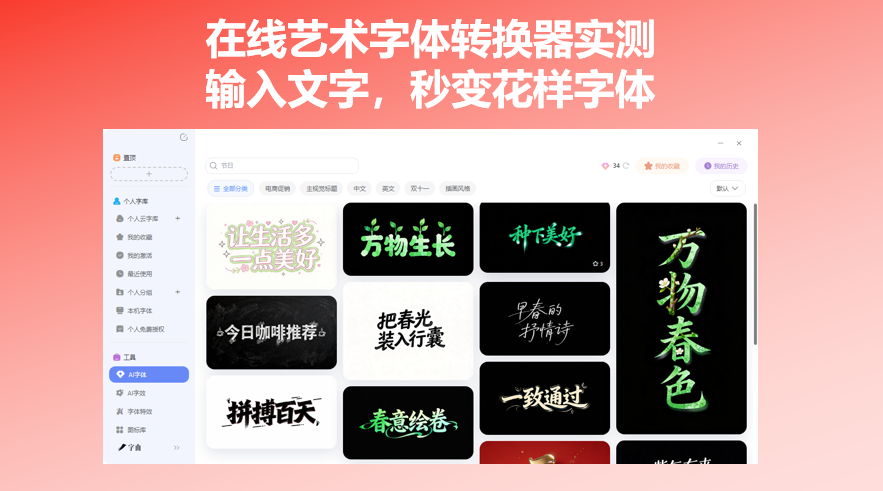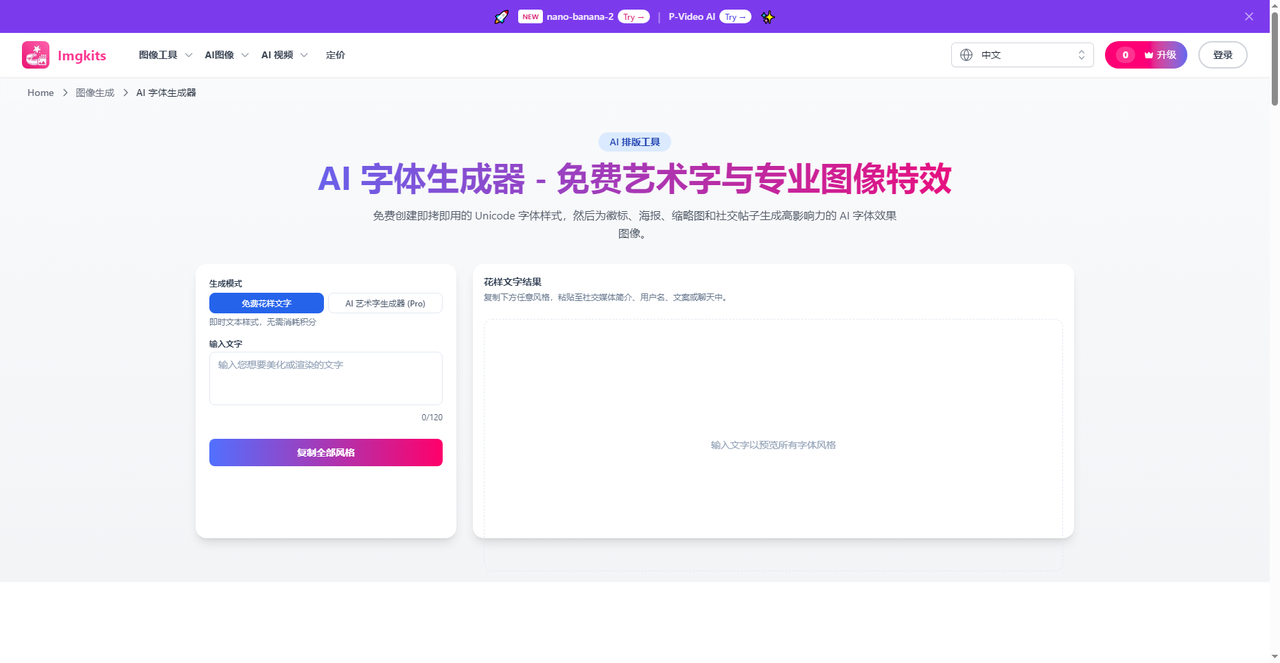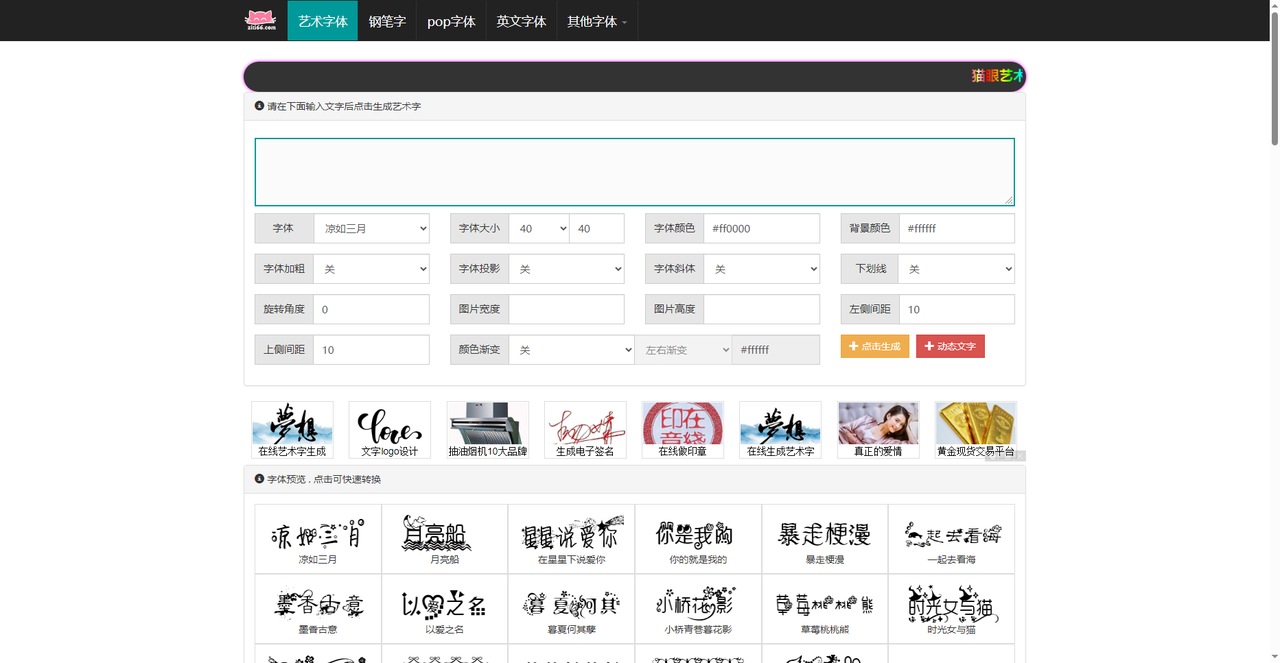
在线艺术字体转换器实测:输入文字,秒变花样字体
你有没有这种经历:文案想用花体字,结果只能打普通字体;做海报标题想要霓虹灯效果,打开PS调了半天还是觉得土土的;像给游戏账号改个特殊昵称,却没有好的办法。不过不用担心,这些问题一个在线艺术字体转换器就能搞定——输入文字,选个样式,复制粘贴或者下载图片,几秒钟完事。今天我的实测了5个不同风格的在线艺术字工具,从AI一键生成到参数自由调节,从Unicode花体到毛笔书法,覆盖了各种使用场景。喜欢的记得收藏!
字由是国内设计师用得最多的字体管理与AI平台之一。它的AI字体功能,本质就是一个在线艺术字体转换器——不需要你懂设计,选个模板,改几个字,10秒出图。打开字由客户端,在顶部“AI工具”里找到AI字体。里面按场景分好了类:国潮风、霓虹灯、金属质感、手写书法、电商促销……目前有400多种模板。操作很简单:先筛选你想要的风格,比如要做一张国潮海报,点“国潮风”分类,所有相关模板列出来;选一个顺眼的,点击“做同款”,在右侧输入框里把模板里的文字换成你自己的文案;点“立即生成”,等待10秒左右,系统就会生成一张带特效的艺术字图片。
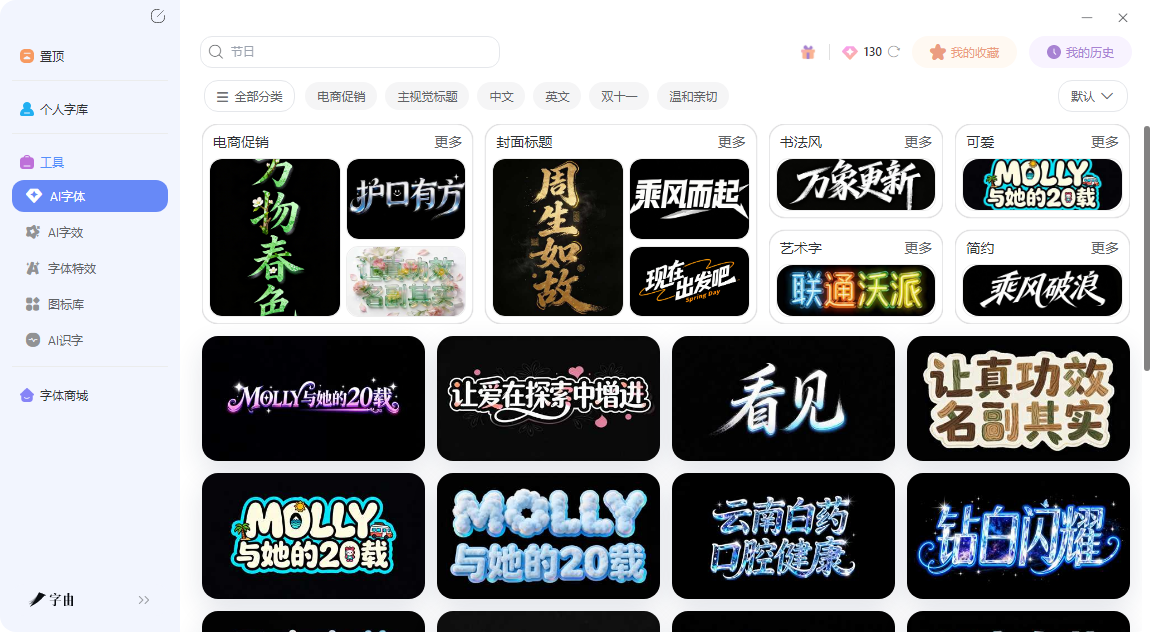
生成后可以下载透明背景的PNG,直接拖进PS、剪映或者海报里。每天登录送免费算力,日常够用。字由的模板质量高,调用的都是正版字体,生成的图片可商用。如果你连字体都懒得挑,或者完全不懂排版,字由的AI字体是最省事的选择。
2、Imgkits
第二个工具是Imgkits。截图显示它有一个“AI字体生成器”功能,但它的核心亮点是“花样文字结果”——输入文字后,系统会生成几十种Unicode花体样式,比如花体、粗体、斜体、哥特体、气泡体等。每种样式旁边都有一个复制按钮,点一下就能复制,然后粘贴到微信、抖音、Instagram、游戏昵称等任何支持文本输入的地方。和生成图片的工具不同,Imgkits输出的是纯文本,所以不挑平台,所有设备都能正常显示。它不需要注册,完全免费。如果你只是想发一条花体字朋友圈、改一个酷炫的游戏昵称,或者给社交媒体简介加点个性,Imgkits比打开PS做图方便太多。
3、猫眼艺术
第三个工具是猫眼艺术。这是一个功能更偏向“设计”的艺术字生成器。它提供了“凉如三月”等多种中文字体,你可以调节字体大小、颜色、背景色、加粗、投影、斜体、下划线、旋转角度、图片尺寸、左右上边距,还支持颜色渐变(左右渐变)。输入文字后点击“生成”,就能看到预览效果,然后下载图片。这个工具适合那些“对花体字不满意,想要更自由控制”的用户。比如你做好了一张海报,标题想用艺术字,但颜色必须和品牌色一致,猫眼艺术可以精确调色;想加投影让字更有立体感,勾选“字体投影”就行。它比纯花体字生成器多了设计自由度,又比PS简单很多。页面下方还有“字体预览”区,点击“凉如三月”“暴走梗漫”“月亮船”等预设字体,可以快速切换样式。
4、艺术字体在线生成器
第四个网站是一个综合型的艺术字体转换器。它的分类很全:毛笔字、艺术字、手写体、英文字体、花体英文、卡通更多。首页展示了“虎年精选字体”“海报字体下载”“电商广告专用字体”“书法字体”“简约字体”“卡通可爱字体”等热门分类。还提供了签名设计功能,输入姓名可以生成连笔签名、花式个性签、国风签名。这个站的特点是“多”——模板多、分类多、场景多。如果你是电商运营,需要经常做促销海报,可以直接在“电商广告专用字体”里翻;如果你做儿童产品设计,可以看“卡通可爱字体”。它还支持在线转换:输入文字,选择字体(如“白棋空心简体”),调节大小和颜色,点击“开始转换”就能生成图片。免费使用,适合快速出图。
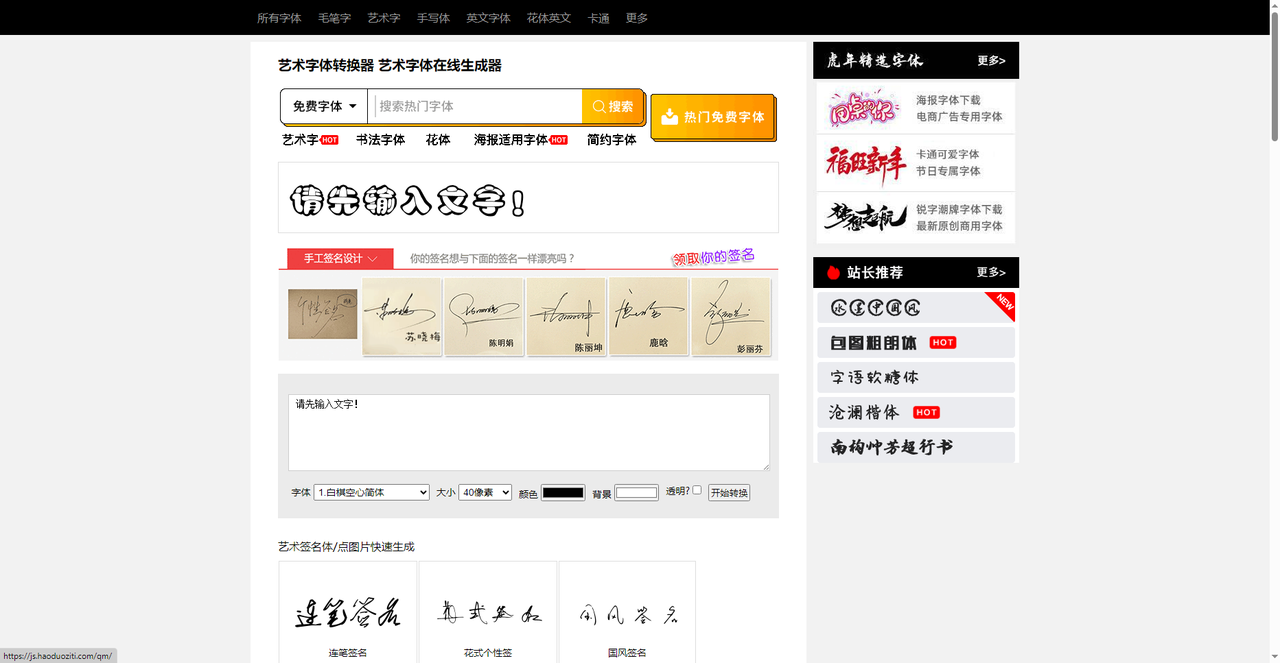
5、第一字体网
第五个工具是第一字体网。它有一个专门的“字体转换器”功能,主打毛笔书法字体和艺术创意字体。首页推荐了“西风烈马手书”“传奇书法字铺”“逍遥双书法体”“可爱熊猫字体”“怀旧电影字体”等。你可以选择字体、字号、行高、背景色(支持透明),然后在线生成预览图,也可以下载图片。第一字体网的特色是“毛笔书法”和“国潮风”。如果你需要做中式招牌、茶叶包装、古风海报的标题字,这里的书法字体比普通艺术字更有味道。比如“西风烈马手书”笔触苍劲有力,“传奇书法字铺”带有碑刻质感。它还提供了“商用授权”入口,方便购买版权。网站统计显示“西风烈马手书”已被转换超过55万次,说明很受欢迎。
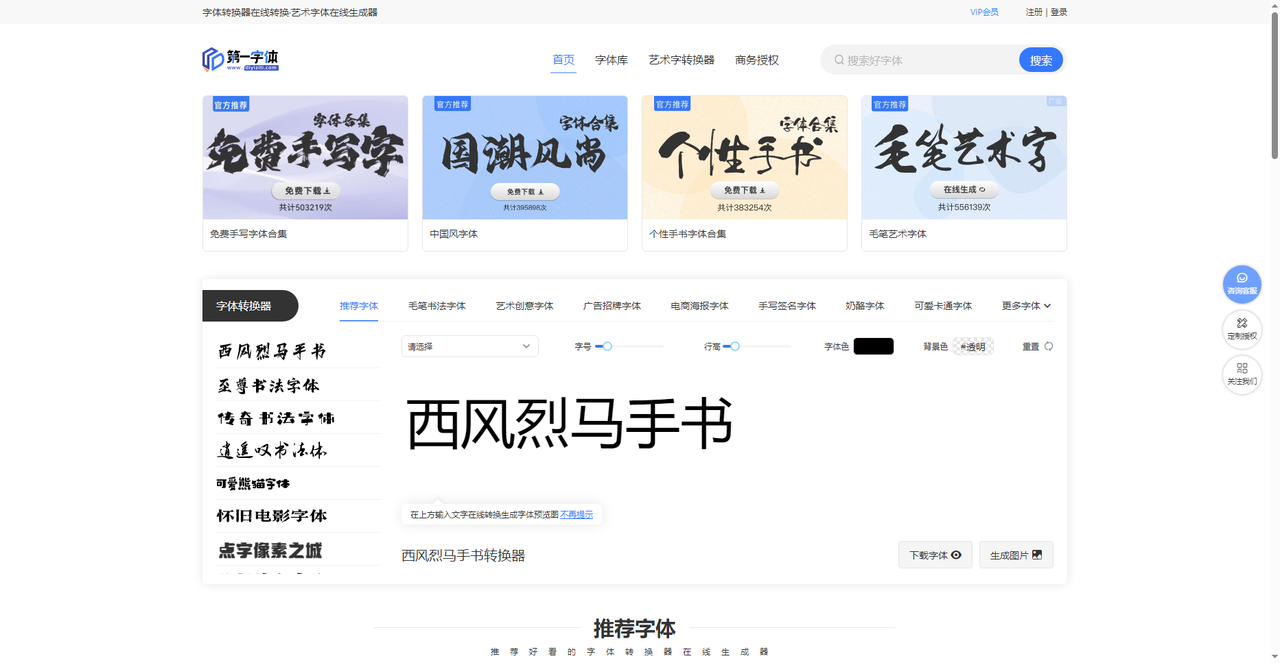
5个工具,5种不同的玩法。字由最适合设计师和需要高质量可商用艺术字图片的人,400多种AI模板10秒出图;Imgkits最适合普通用户复制粘贴花体字到社交平台;猫眼艺术支持颜色、大小、投影、渐变等参数调节,适合对设计有要求但又不想学PS的人;第四个网站模板海量,分类齐全,适合按场景快速找字体;第一字体网专注毛笔书法和国潮风,适合中式设计项目。选哪个取决于你当下的需求——是要图片还是纯文本,是要花体字还是毛笔字,是做海报还是发朋友圈。这几个工具基本都是免费的,挨个试一遍,输入文字就能看到效果,希望可以帮到你。